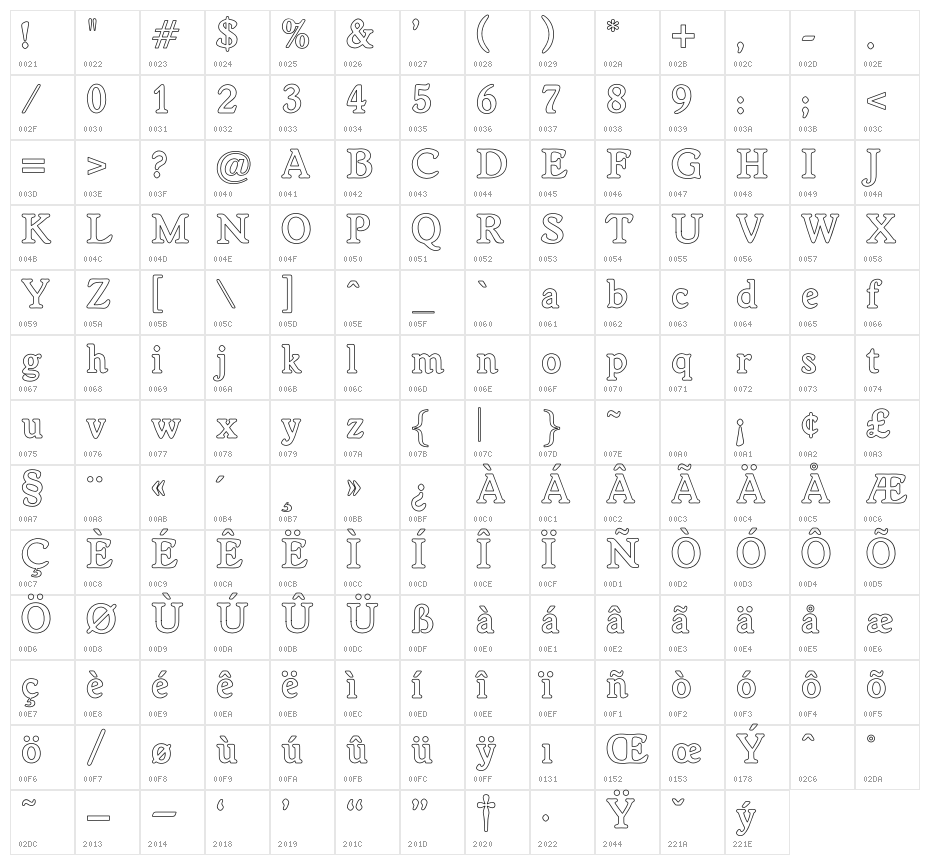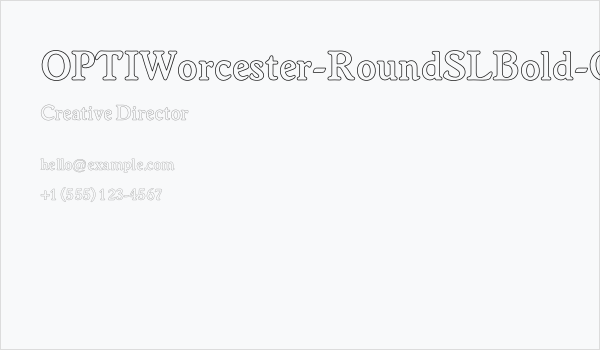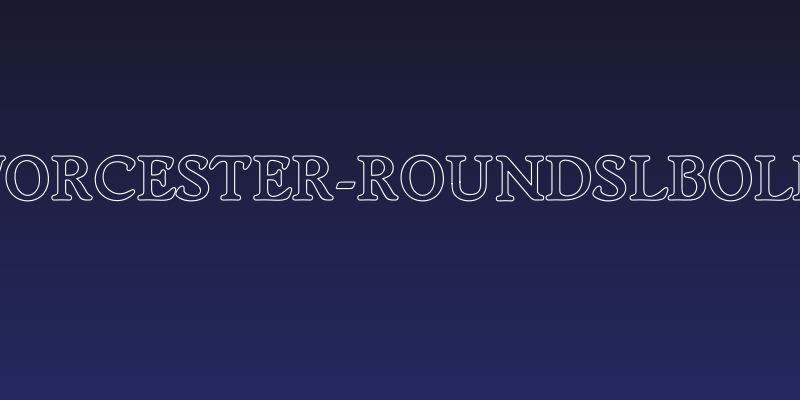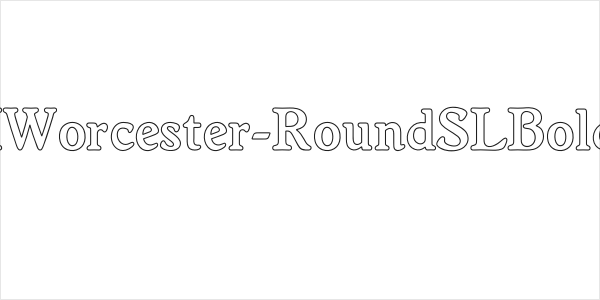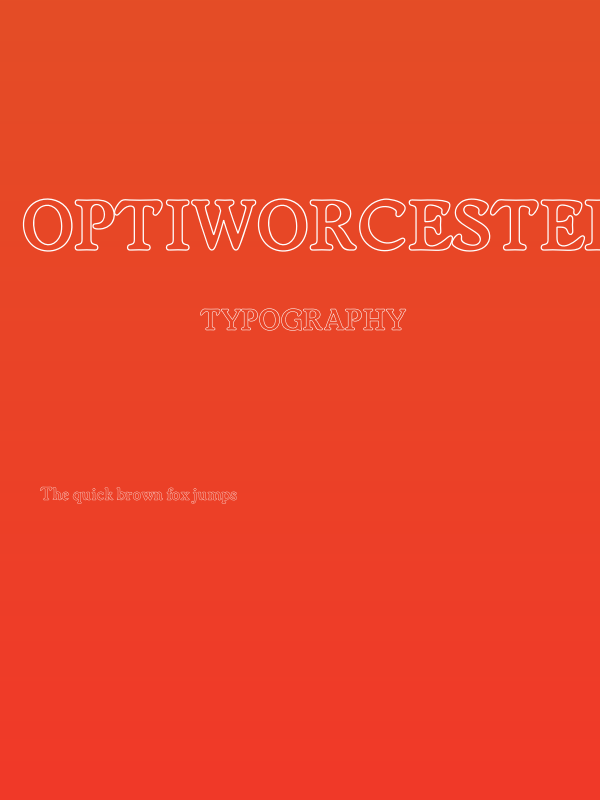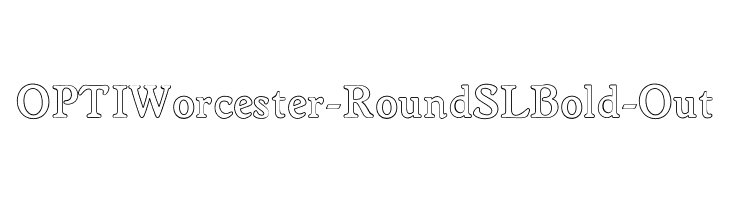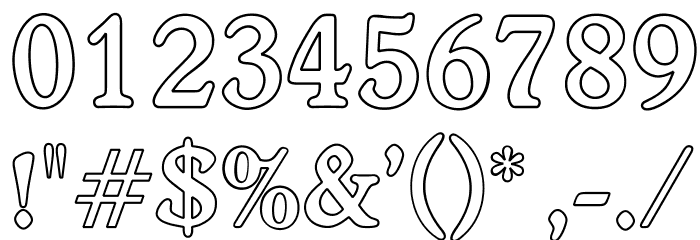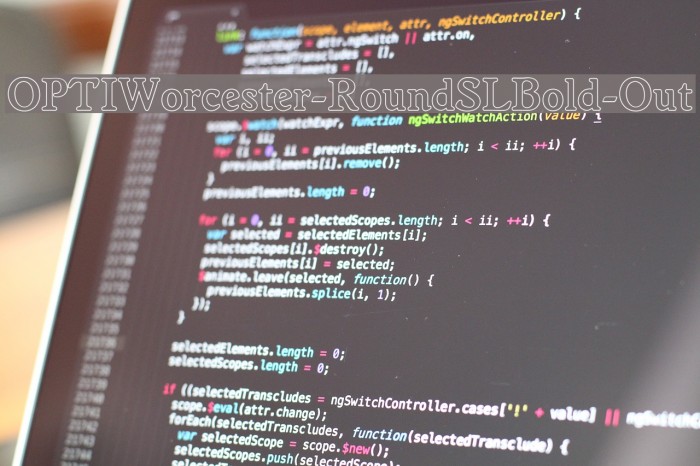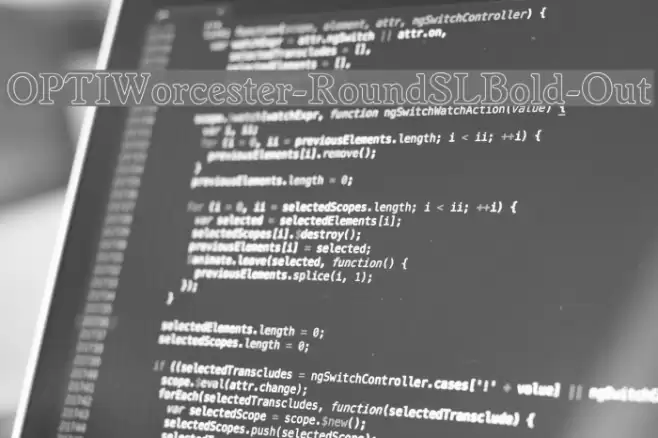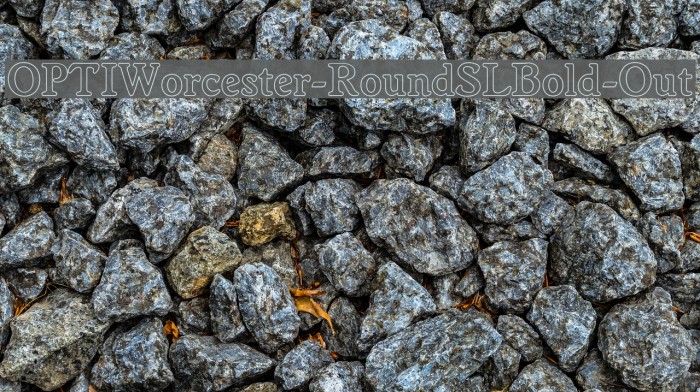
OPTIWorcester-RoundSLBold-Out Font
| حالة الاستخدام | Headlines, Logos, Branding |
| مشاريع مقترحة | Ideal for branding, signage, packaging, and digital media where a friendly yet professional look is desired. |